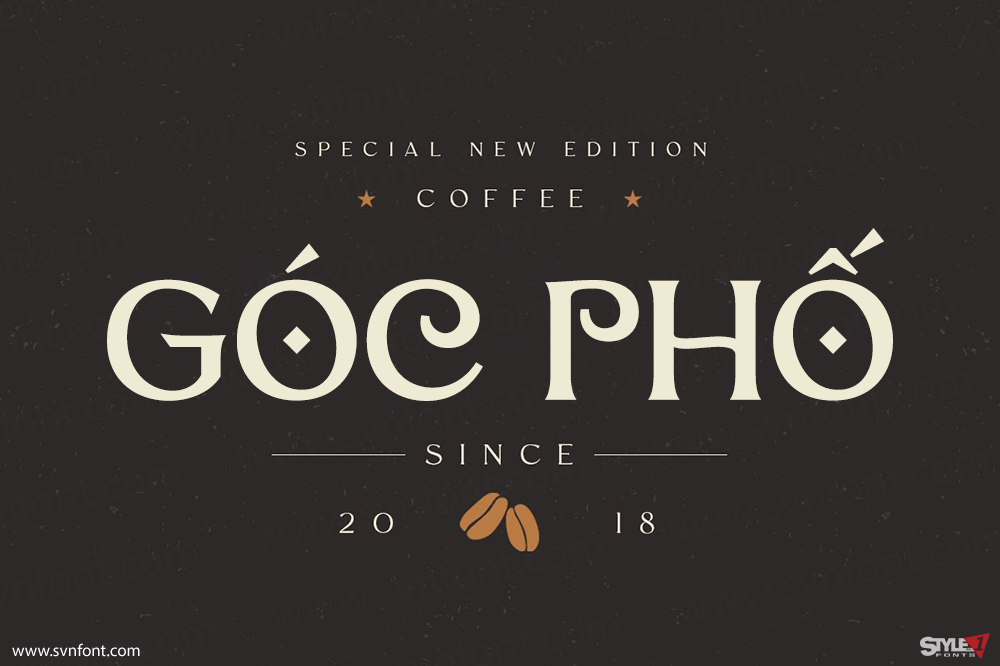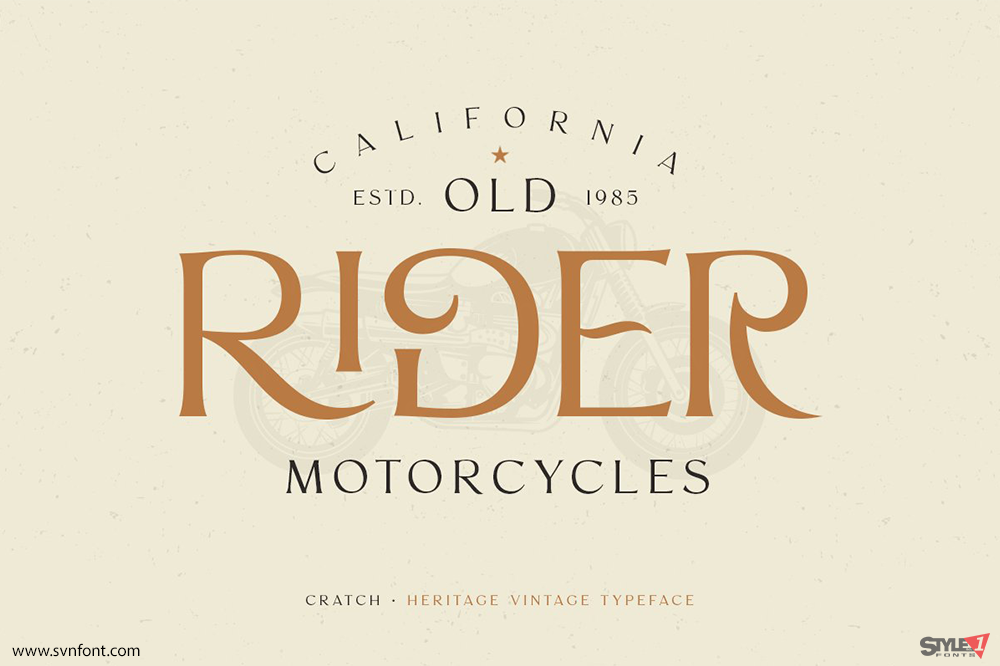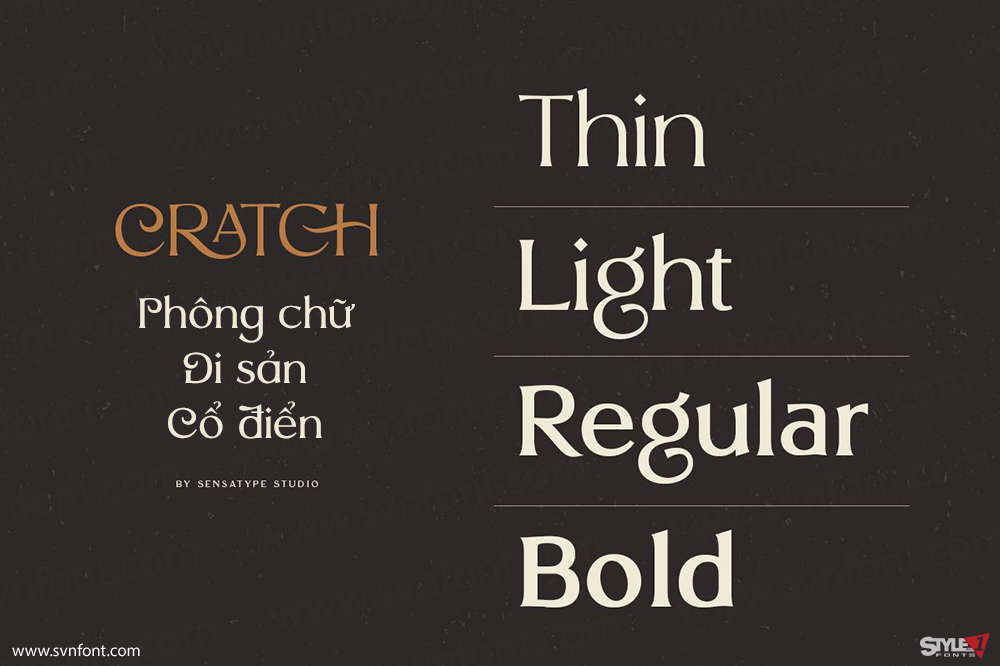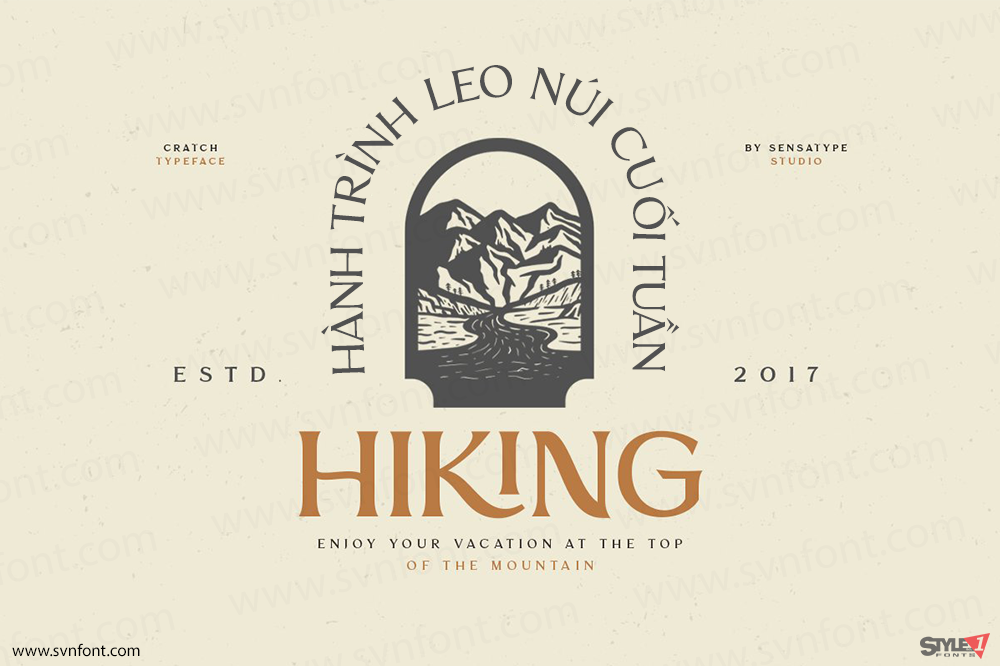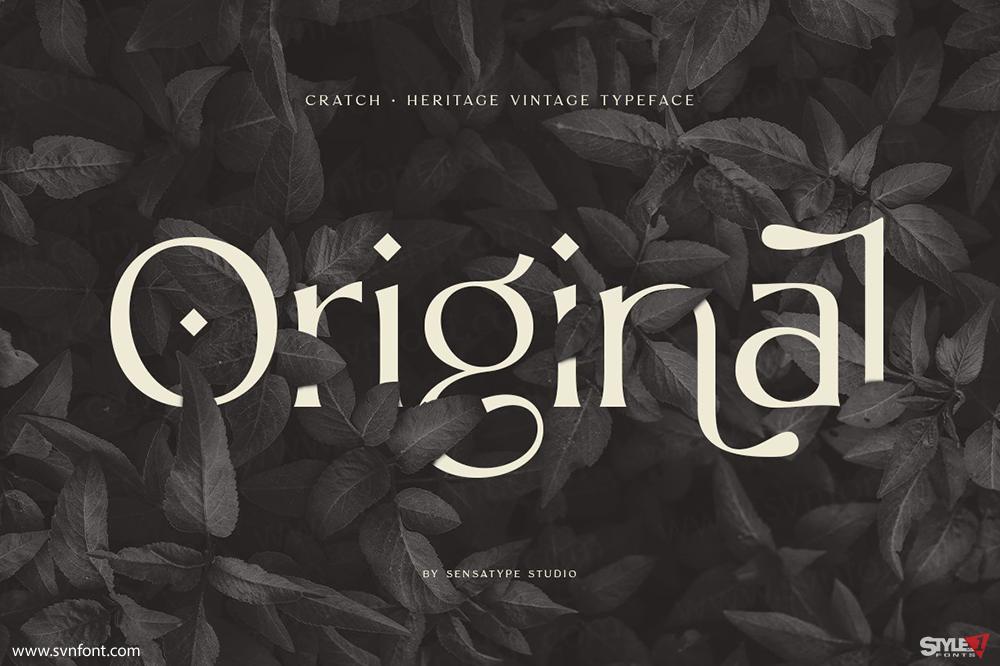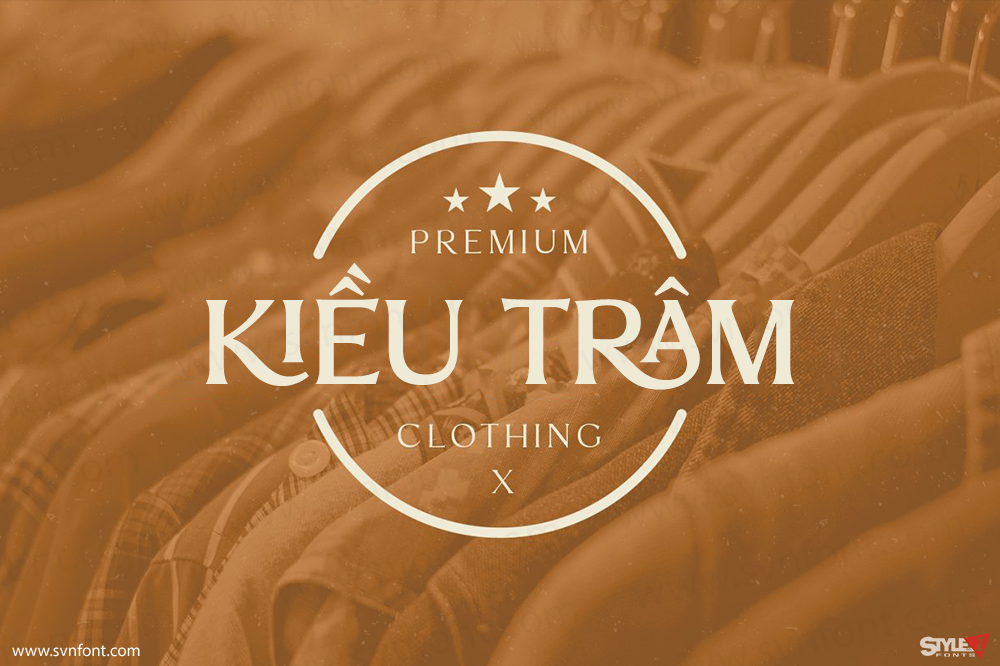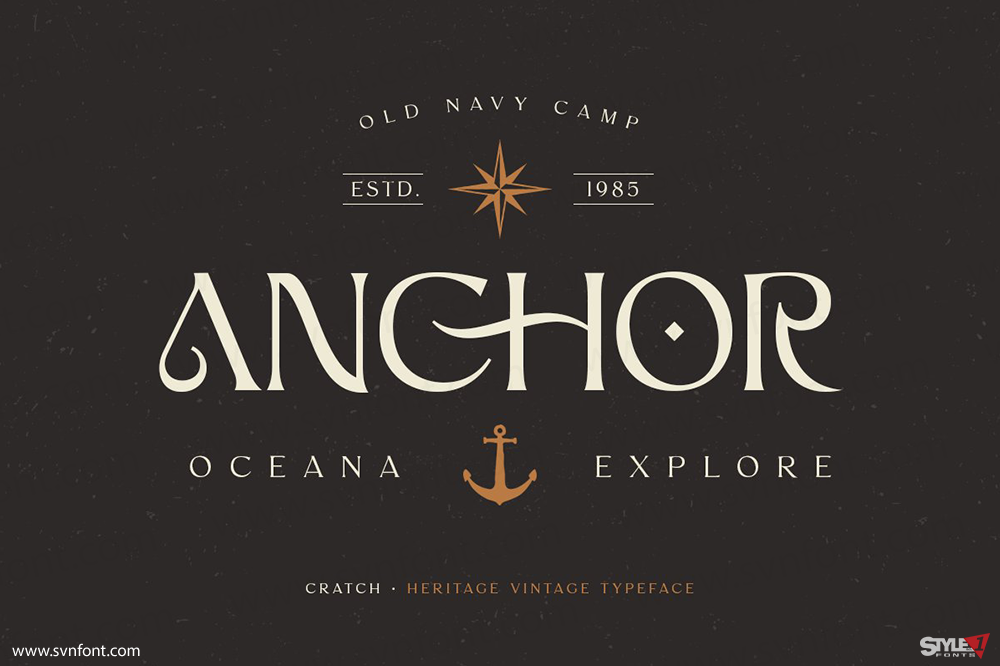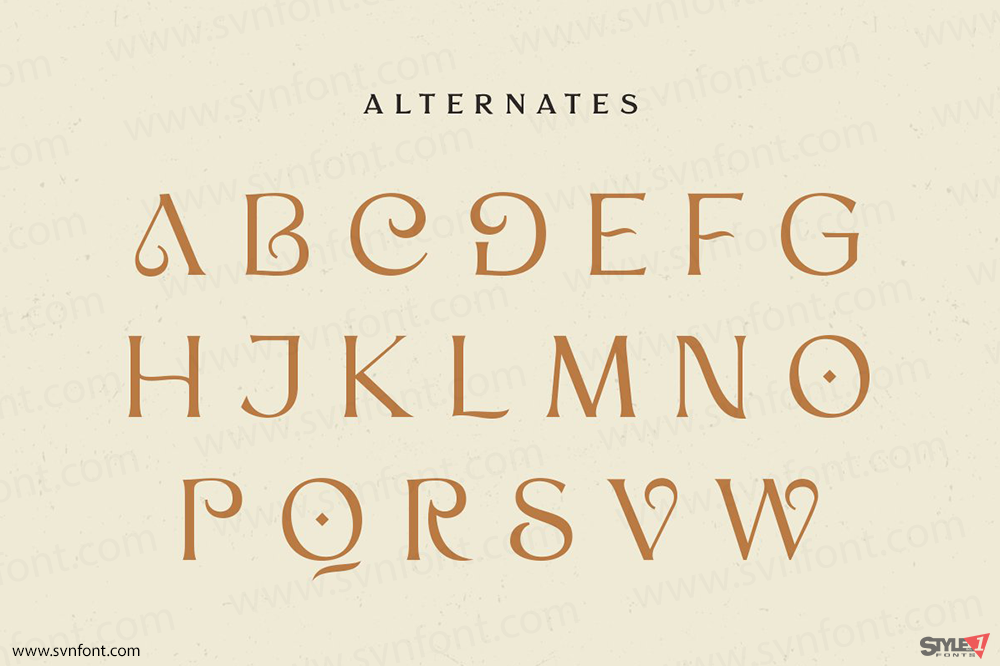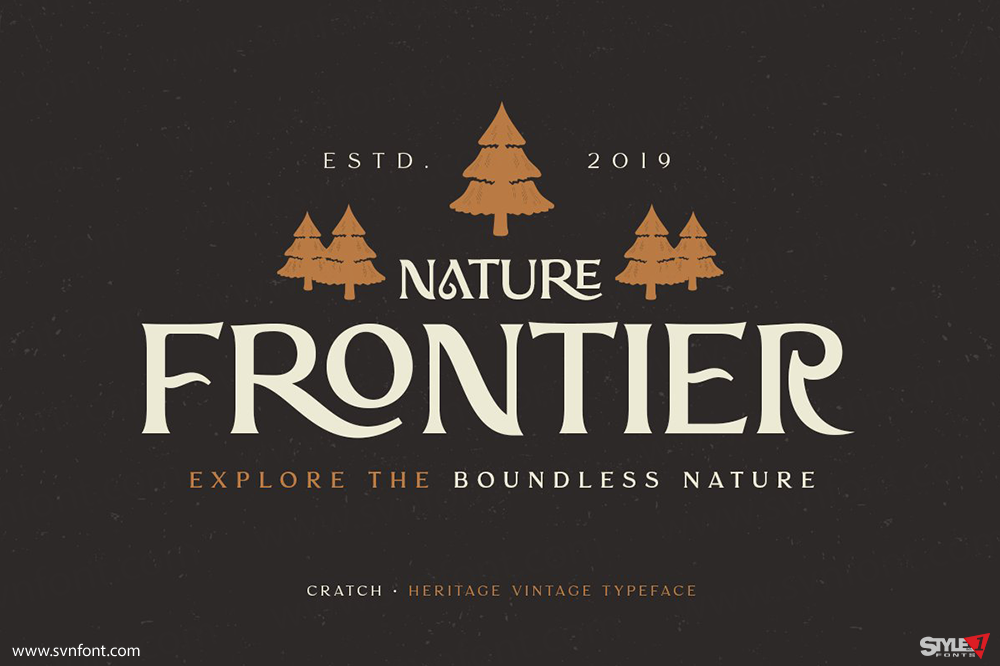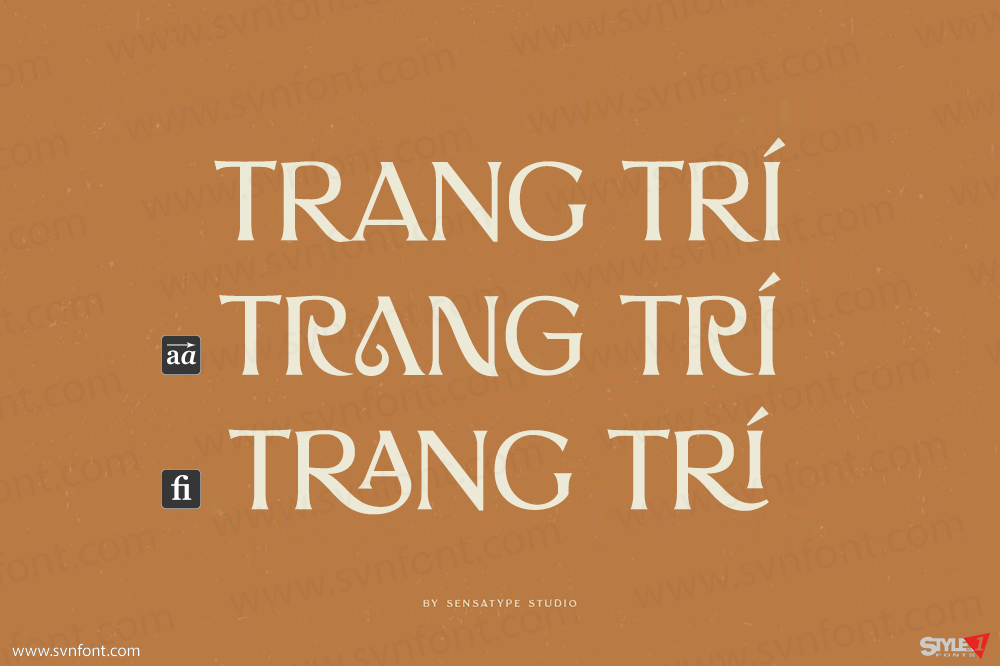
Cratch Vintage là một font chữ đương đại cân đối với kiểu chữ serif vintage độc đáo, lạ mắt và linh hoạt mà bạn có thể kết hợp để có được bất kỳ biến thể và hình dạng độc đáo nào một cách dễ dàng chỉ trong vài giây. Đây là một font chữ hiển thị serif với độ tương phản vừa phải, hoàn hảo cho các dự án thương hiệu, logo, thiết kế đám cưới, bài đăng trên mạng xã hội, quảng cáo, bao bì sản phẩm, thiết kế sản phẩm, nhãn mác, nhiếp ảnh, hình mờ, thiệp mời, văn phòng phẩm và bất kỳ dự án nào. Font này được tạo ra với mức độ dễ đọc cao.
Nhà thiết kế: Zamroni Hamzah
Nhà phát hành: Sensatype